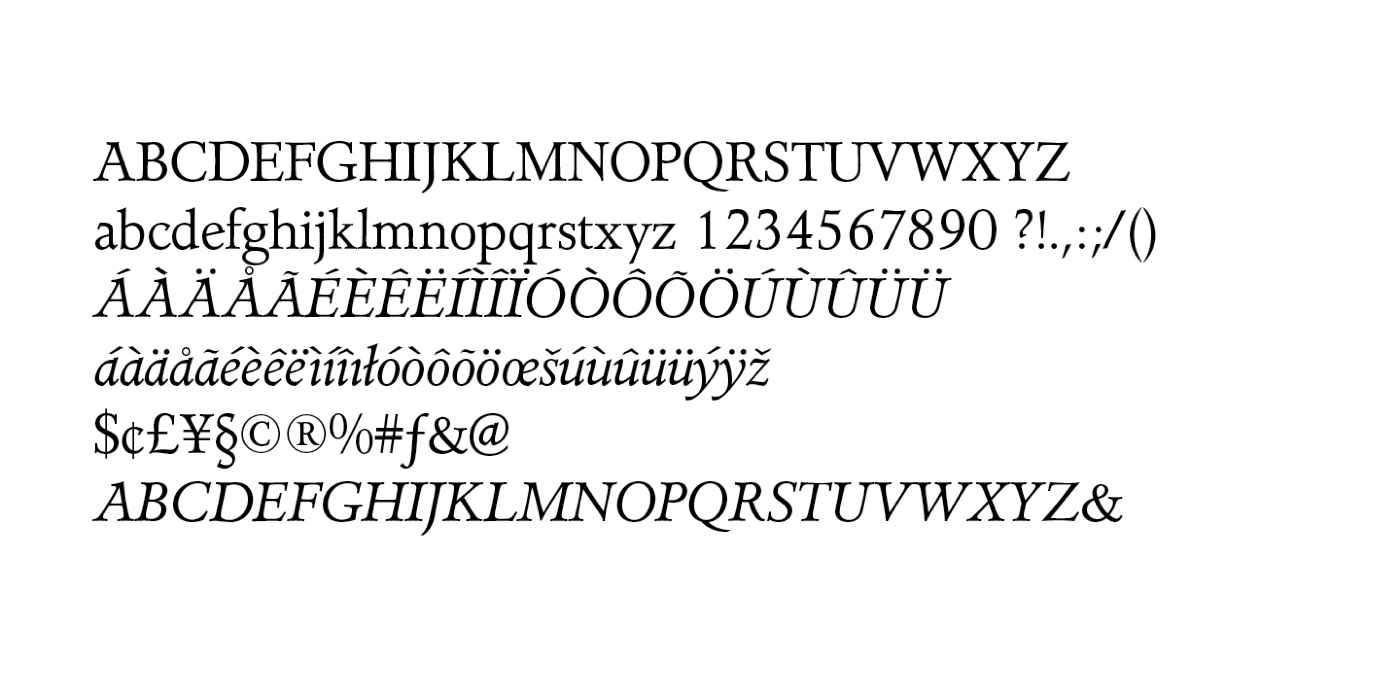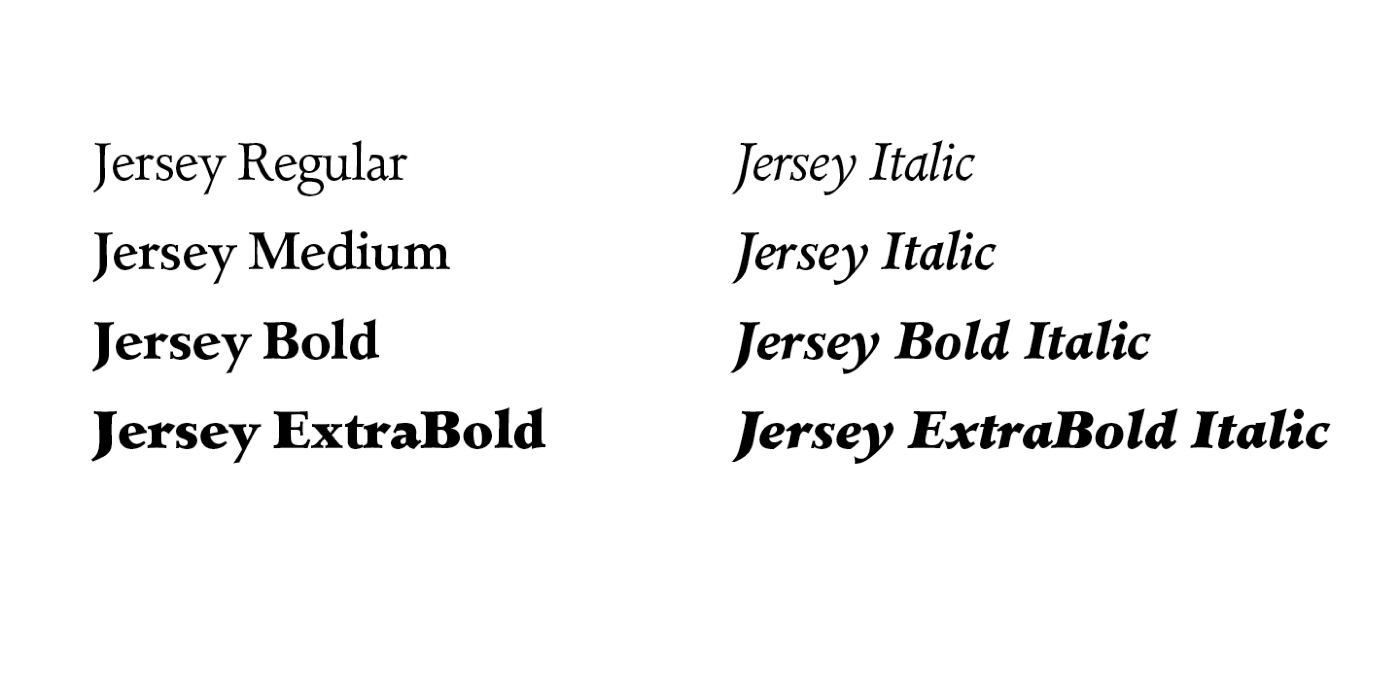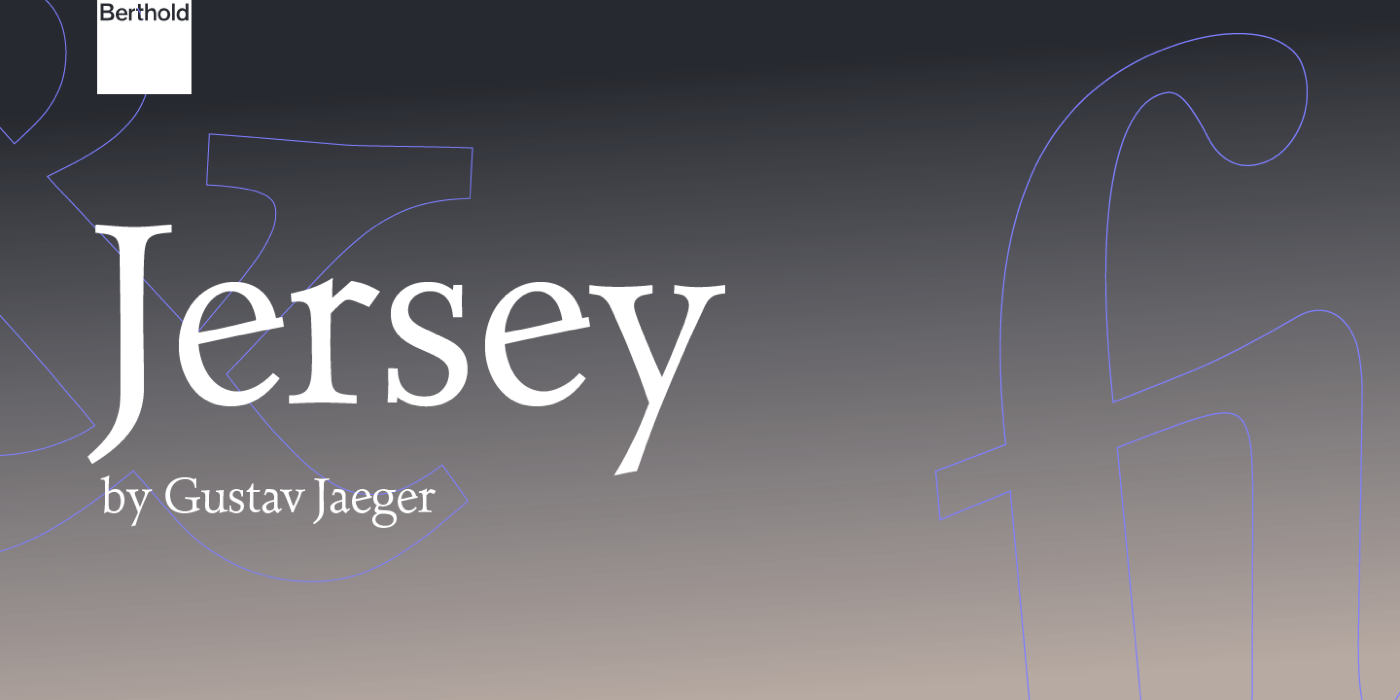
Die Jersey ist eine humanistische Antiqua-Familie mit kantigem Schnitt, der insbesondere in den fetteren Schnitten zur Geltung kommt. Die Schrift aus den 1980er-Jahren ist heute in vier Strichstärken mit Kursiven und westeuropäischer Zeichenbelegung verfügbar.